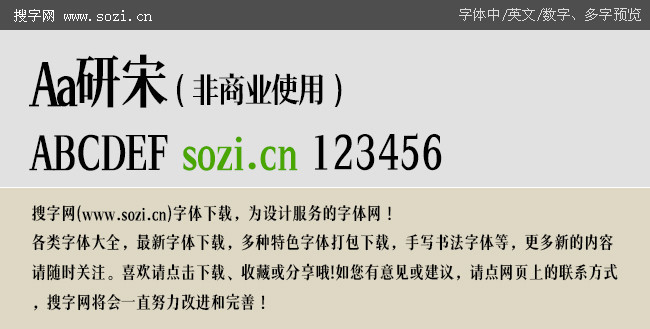
Aa研宋
搜字網(wǎng)給大家提供一款A(yù)a研宋(非商業(yè)使用)中文字體下載,該字體是一款宋體字體,字體風(fēng)格簡潔大方,字形端正,具有很好的視覺感,適用于平面宣傳設(shè)計、網(wǎng)頁設(shè)計、海報設(shè)計等應(yīng)用(此字體為個人非商用版,商用可以聯(lián)系QQ:1006760504)。